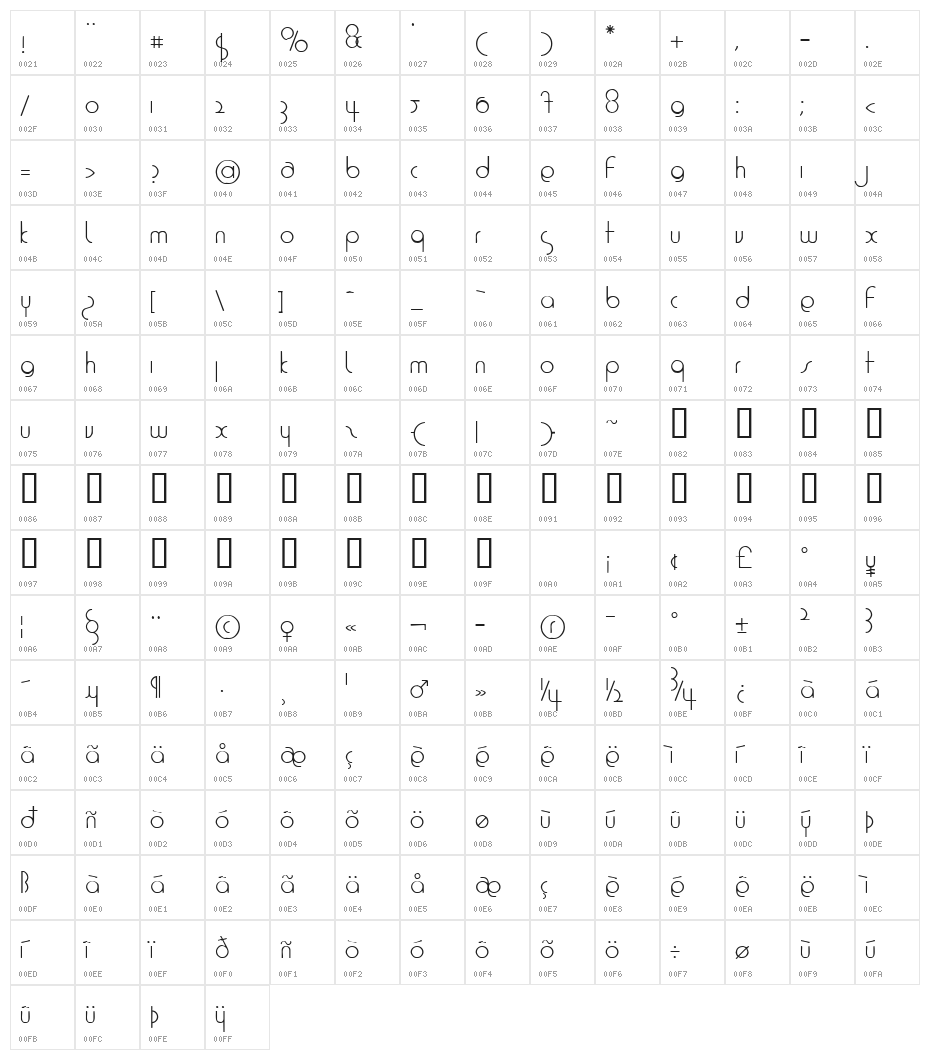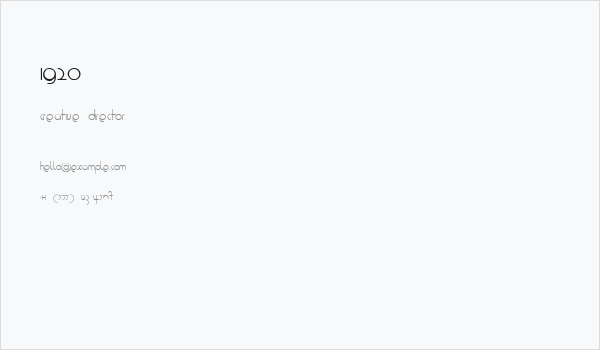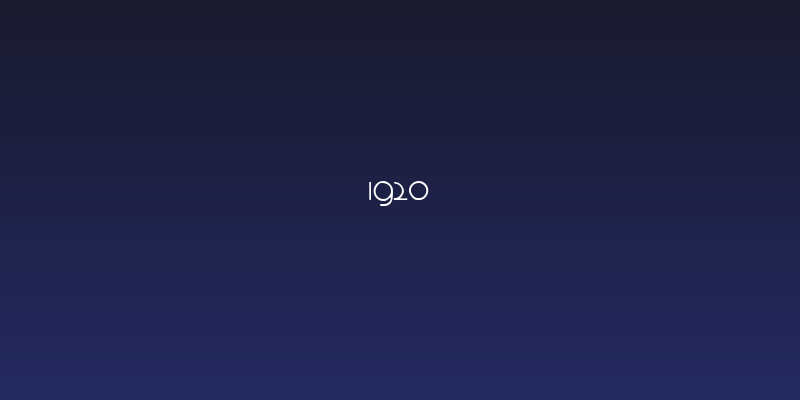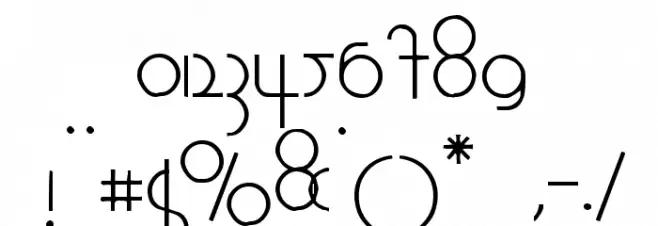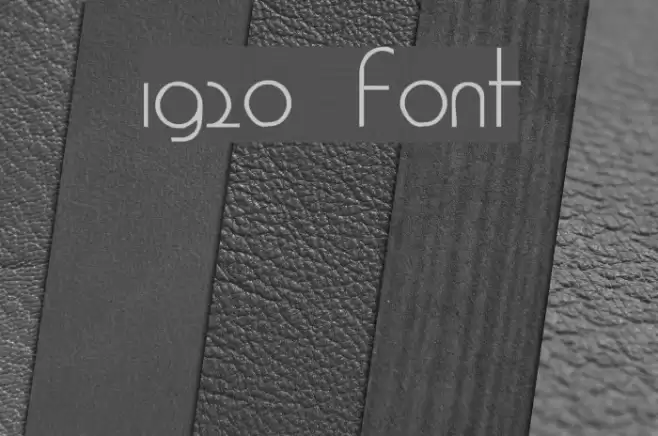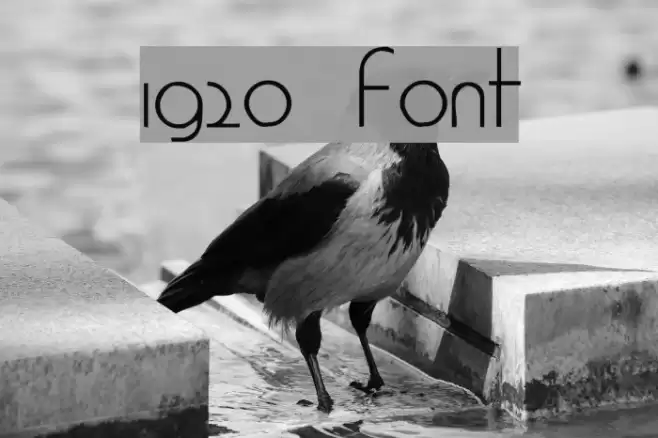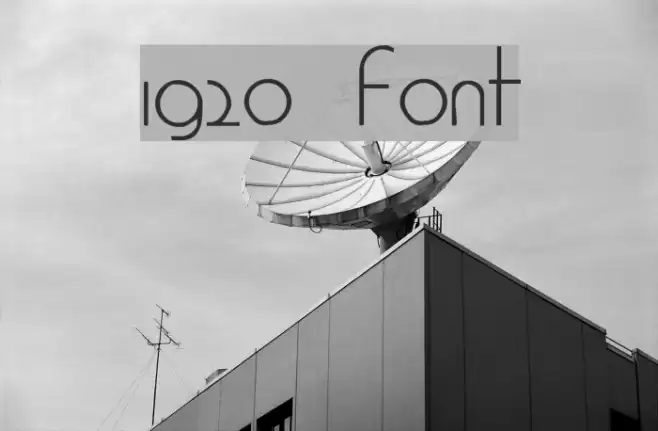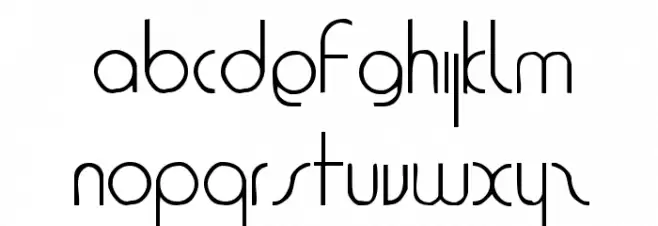
1920 Font
| Anwendungsfall | Logos, Posters, Digital Media |
| Vorgeschlagene Projekte | Ideal for branding, logos, posters, and digital media projects that require a modern and sleek aesthetic. |